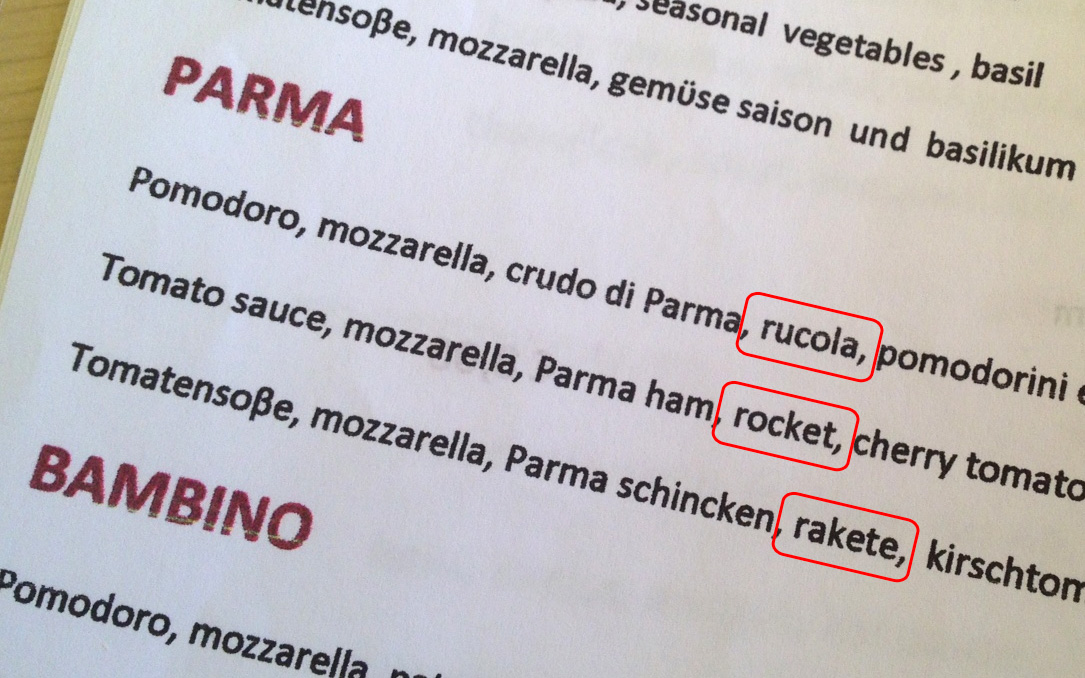
muss gar nicht aus dem haus gehen deswegen. es reicht schon, die abendnachrichten zu schauen und der blutdruck steigt wegen verhunzter inserts mit zollzeichen als anführungszeichen.
Ich heiße Peter, und habe eine „Fraktur-ohne-langes-s-und-misbrauchtem-tz-statt-k-intolereanz“ und ich ertappe mich beim betrachten von Plakaten, Werbeflyern und Filmvorspannen dabei, statt über das Produkt oder den Film, über die Schrift nachzudenken.
Geht mir bei Speisekarten so, egal, ob im Inland oder Ausland. Ich überlege, ob die Schrift zur kulinarischen Ausrichtung des Restaurants passt, ob sie bei der vorhandenen Beleuchtung und/oder für Gäste mit schlechten Augen überhaupt lesbar ist, und warum keiner, der der Sprache halbwegs mächtig ist, vor dem Druck mal korrekturlesen durfte …
Leider weiß ich nach einer halben Stunde intensiver Lektüre oft immer noch nicht, was ich eigentlich essen möchte …
Pure belly clearance?  Na, da kann man sich ja denken, welche Wirkung dieses Gericht haben könnte... Mann sollte nicht zuweit entfernt der Nasszelle mit dem Keramik-Gestühl sein :-)
Ja genau, oder sowas hier:
Bei uns in der Kantine gab's mal "Leibzigerallerlei" … Hab aber leider das Bild gerade nicht parat (irgendwie wundern die sich auch immer, wenn ich am Schalter in der Schlage stehe und die Schilder mit den Namen der Gerichte für meine best-of-Kollektion abfotografiere …).
Weiteres Hobby:
Mich in Jachthäfen darüber aufregen, dass manche Eigner die Namen ihrer Edel-Boote aus Großbuchstaben einer Script-Schrift zusammenbasteln. Das sieht mal besch…eiden aus!
Ich hatte mal eine rumänische Speisekarte in der Hand, in der »Makkaroni« mit »Isolierschlauch« übersetzt war. Kein Scherz.
Das kommt wahrscheinlich dabei raus, wenn man zum Übersetzen diese OhneWörterBücher mit Zeigebildern benutzt …